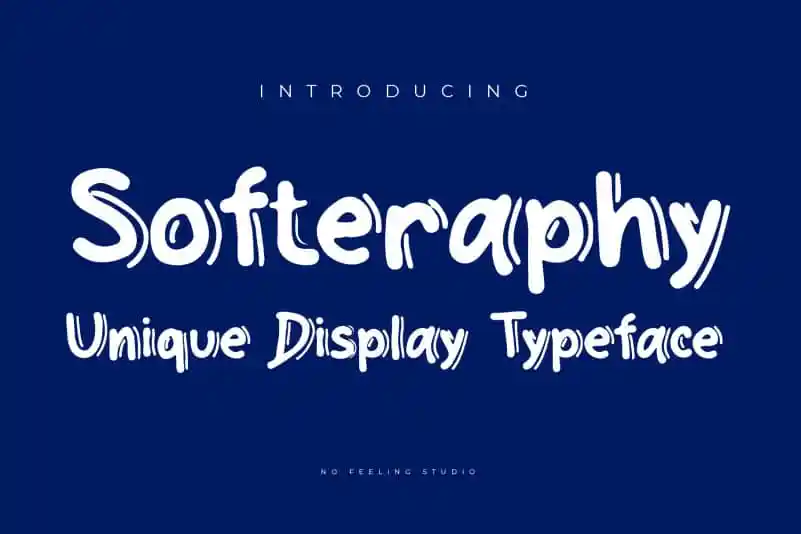
A Softeraphy Display Font é uma tipografia ideal para criar projetos divertidos e frescos. Ela traz características únicas do tipo exibição, desenhada no estilo de quadrinhos para deixar qualquer projeto mais alegre e vibrante. Esta fonte oferece um toque único que pode ser incorporado em diversos projetos gráficos – desde cartazes e identidades corporativas até designs de livros infantis. Com Softeraphy Display Font, seus projetos certamente serão mais divertidos e desafiadores! Escolha esta fonte para imprimir seu próximo projeto, garantindo que ele seja atraente e inovador sem sair do lugar.